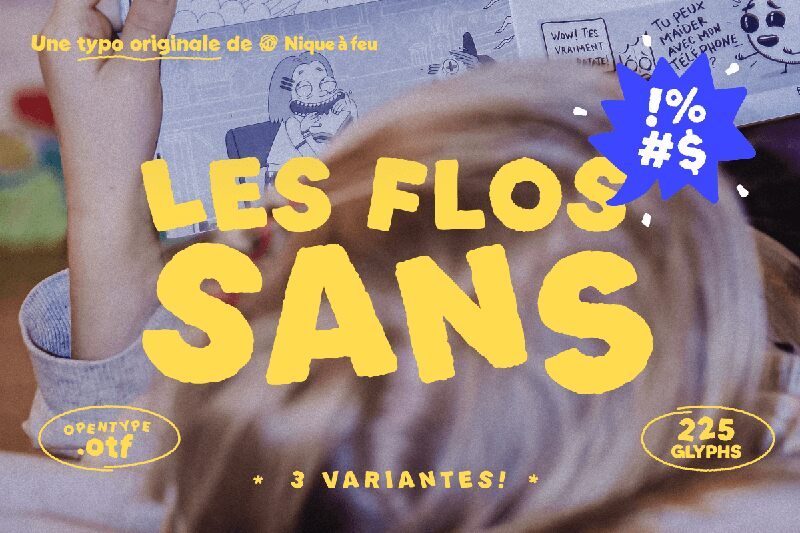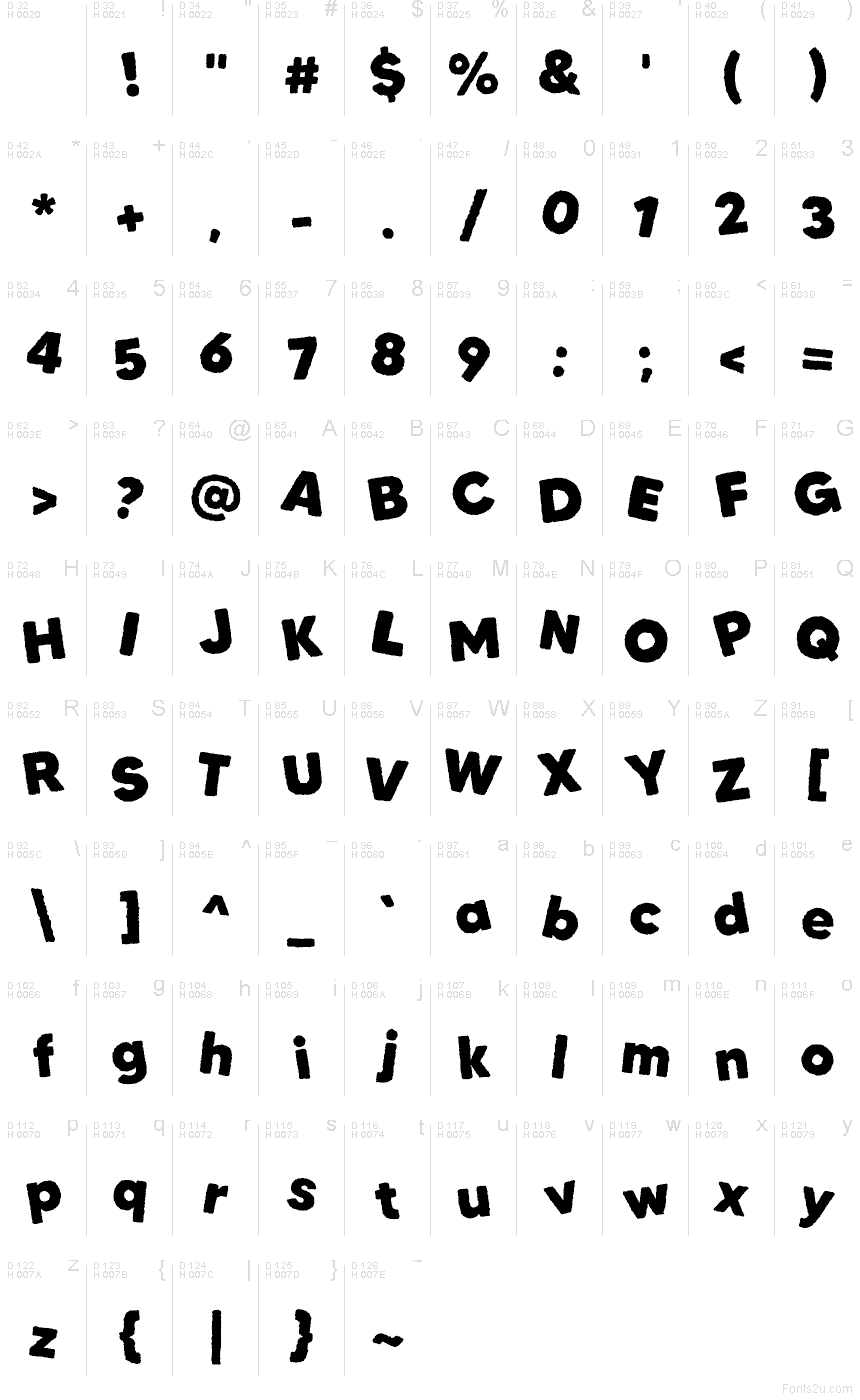
Les Flos Chaos von Nique à Feu ist eine kostenlose Cartoon-Display-Schrift mit schiefen, knubbeligen Buchstaben, die wie aus Schaumstoff geschnitten und leicht aus der Reihe getanzt wirken. Die rauen Kanten und die unebene Strichstärke halten das Schriftbild locker und frech, während die großen, gedrungenen Formen der Schrift eine lebendige, kindliche Energie verleihen – ganz ohne den glatten Look klassischer Comics.
Das macht diese kostenlose Schrift zur idealen Wahl für Zines, Plakate für Kinderveranstaltungen, Snack-Verpackungen, verspieltes Merch und DIY-Cover, bei denen ein allzu ordentliches Layout fehl am Platz wäre. Nutzen Sie sie für kurze Überschriften, Namen und knackige Branding-Akzente, wenn die Typografie selbst für den Spaßfaktor sorgen soll.
Les Flos ist eine Schrift, die direkt von dem gleichnamigen quebeckischen Buchspiel inspiriert wurde. Sie greift die hybride Form eines Fanzines und eines Jugend-Comics auf.